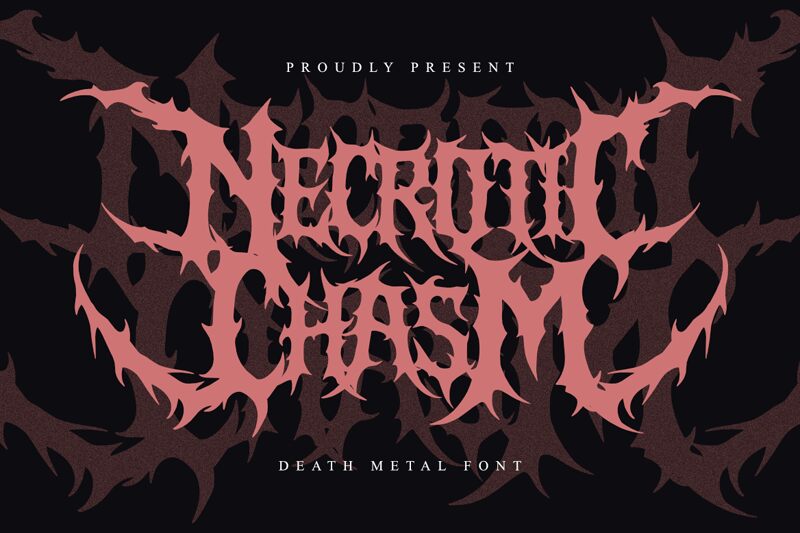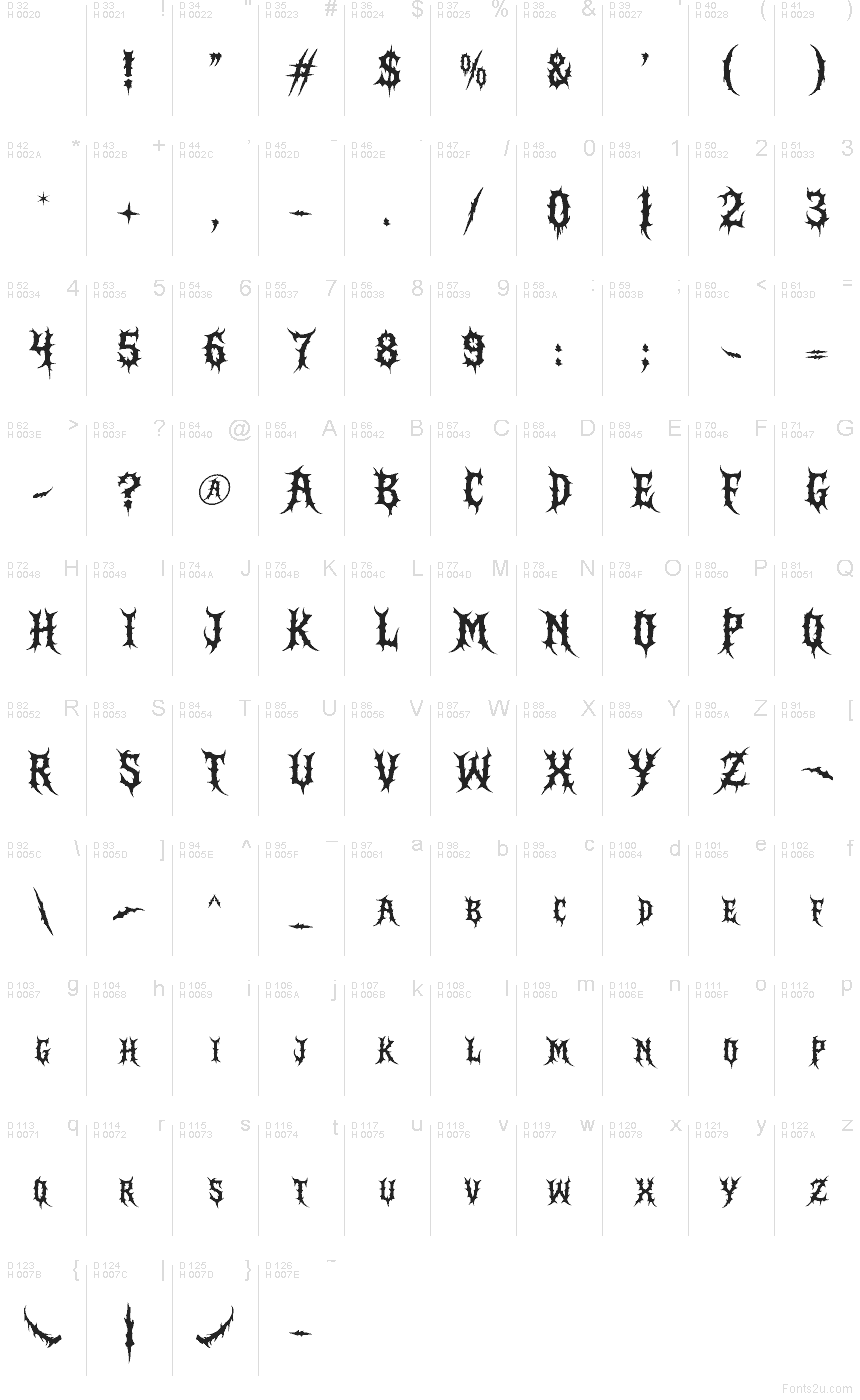
Necrotic Chasm
Font Necrotic Chasm od Masyafi Studio je bezplatné gotické písmo s ostrými, trnitými tvary, které se rozpadají do řezaných hran a zkroucených hrotů. Písmo působí rozervaně a nepravidelně, s frakturovaným rytmem, který dodává slovům temný a agresivní nádech, aniž by potřebovalo další dekorace.
Necrotic Chasm skvěle funguje v názvech hororových filmů, grafice metalových kapel, herních plakátech, přebalech alb či halloweenských vizuálech, protože jeho rozbitá silueta nese silný tematický náboj sama o sobě. Tento bezplatný font se také hodí pro letáky na akce, gotická loga a dekorativní obaly, kdy design vyžaduje drsný, strašidelný akcent namísto běžného písma.